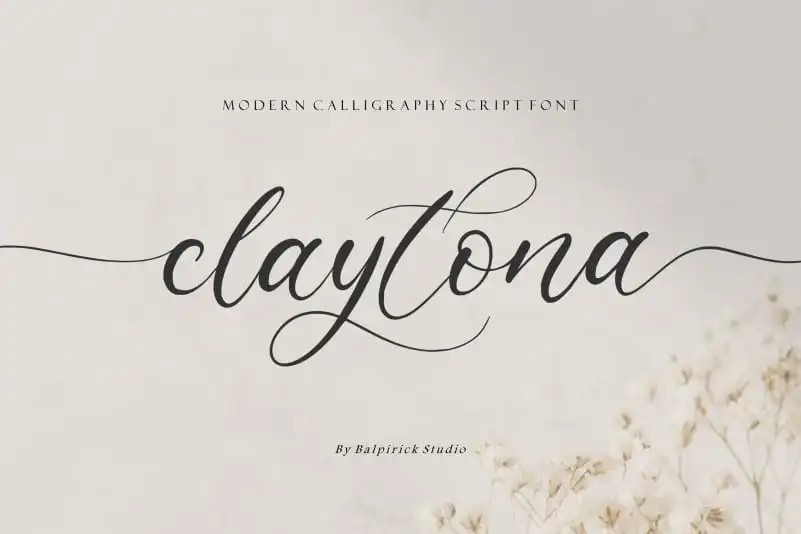
Claytona Calligraphy Font – Download Grátis
A Claytona Calligraphy Font é perfeita para aqueles que buscam uma fonte elegante e envolvente para seus projetos digitais. Suas linhas suaves e delicadas são ideais para criações de branding, embalagens de produtos ou até mesmo as legendas em suas publicações nas redes sociais, expressando um toque único no contexto do fundo. Ideal tanto para editoriais como eventos como casamentos, Claytona oferece uma textura perfeita que adiciona um ar romântico e sofisticado a qualquer design. Suas linhas finas e detalhes sutis trazem um estilo autêntico à sua marca ou conteúdo digital. Não importa o uso específico, seja para criar um visual de marca ou simplesmente expressar palavras no topo de uma página, Claytona é capaz de destacar a mensagem com estilo. Com seu design cuidadosamente elaborado, esta fonte oferece opções para quem busca se destacar em seus projetos digitais, proporcionando um equilíbrio entre elegância e personalidade. É uma escolha ideal para designers que buscam trazer um toque especial a suas criações digitais.